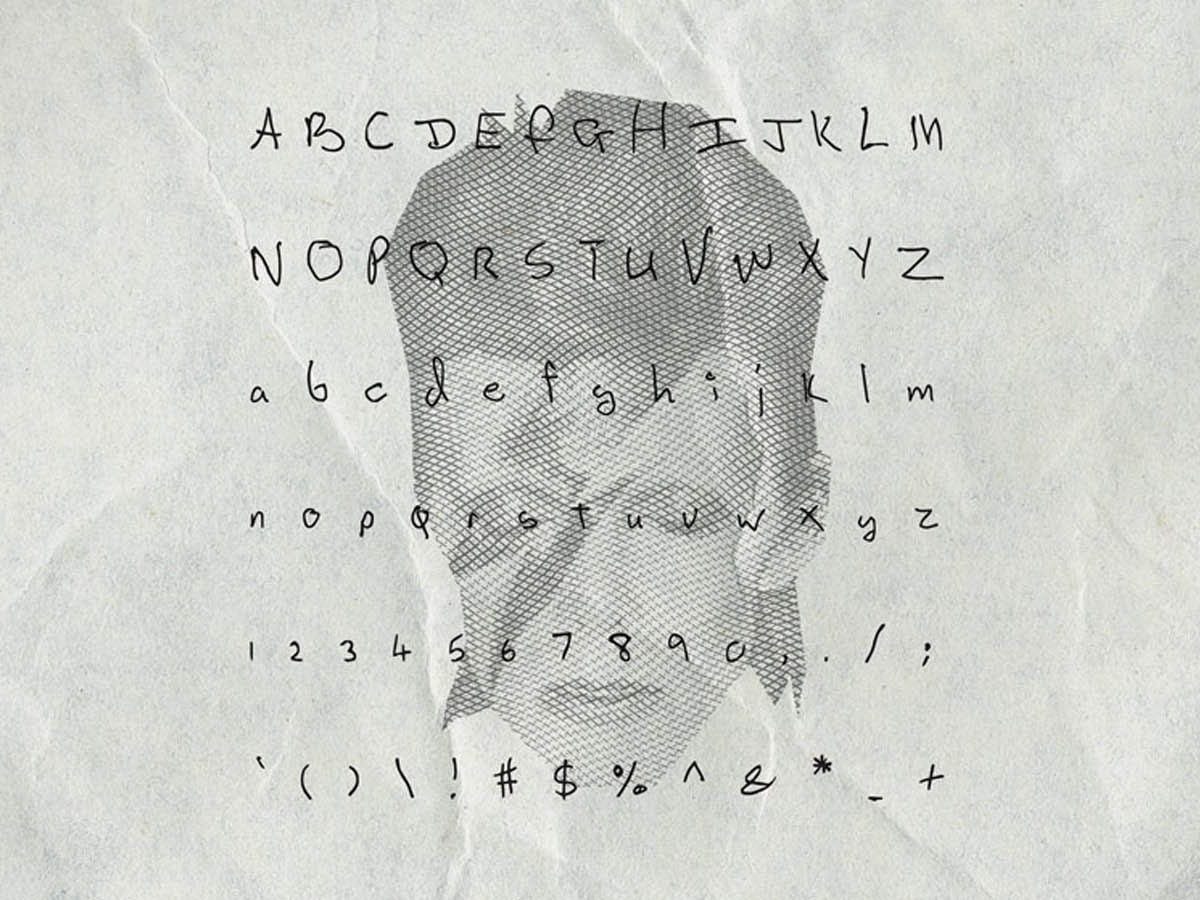
Debut y despedida para SongwritersFonts, el proyecto de Julien Sens y Nicolas Damiens
Los diseñadores gráficos Julien Sens y Nicolas Damiens son los creadores de SongWritersFonts, un proyecto en el que transformaron la caligrafía de célebres músicos en tipografías de descarga gratuita. Instalada en Nueva York, la dupla pasó meses desarrollando las cinco fuentes, a partir de la letra original obtenida de cartas y notas escritas a mano por músicos como David Bowie, John Lennon, Kurt Cobain, Leonard Cohen y Serge Gainsbourg. Sin embargo, poco tiempo después de su presentación, la iniciativa captó la atención de representantes de los derechos de propiedad intelectual, situación que forzó a los diseñadores franceses a eliminar su trabajo. “Hemos lanzado SongwritersFonts como un proyecto de diseño. El único propósito era inspirar a músicos y compositores, pero el inesperado éxito de la iniciativa fue un poco lejos… Hemos sido contactados por los propietarios de los derechos intelectuales, y nos entristece anunciar que debemos cerrar este sitio por cuestiones legales”, explicaron en su mensaje de despedida.